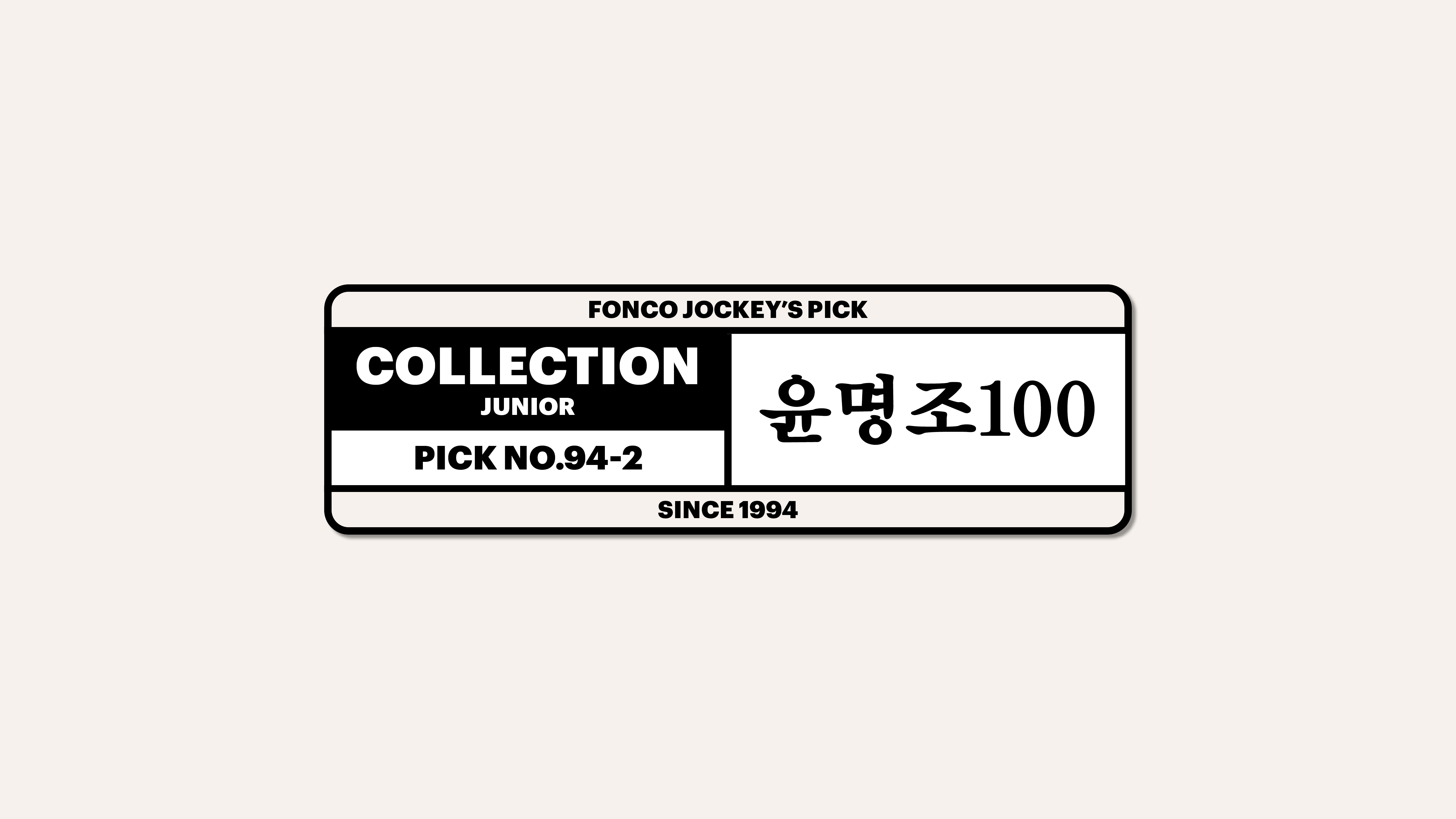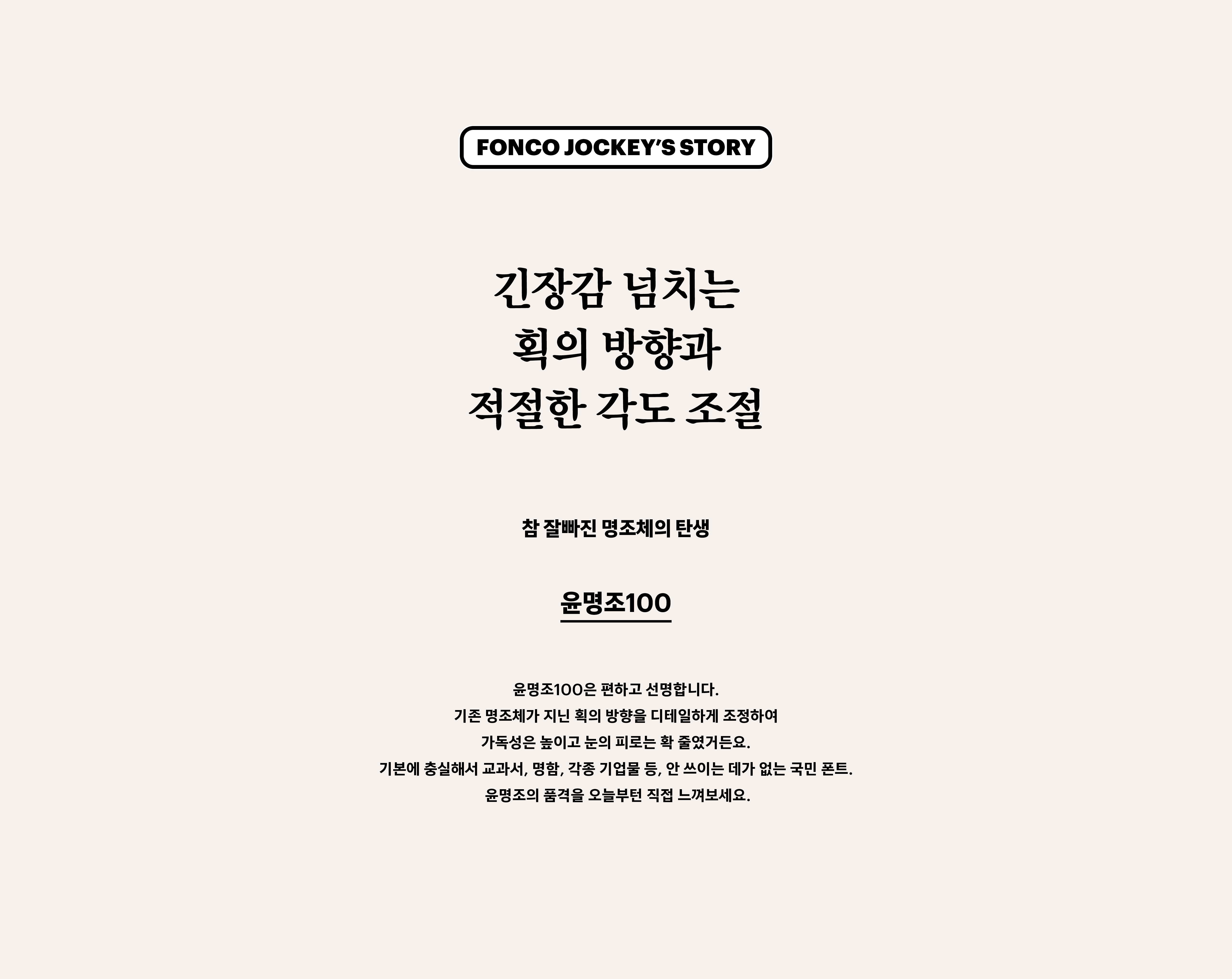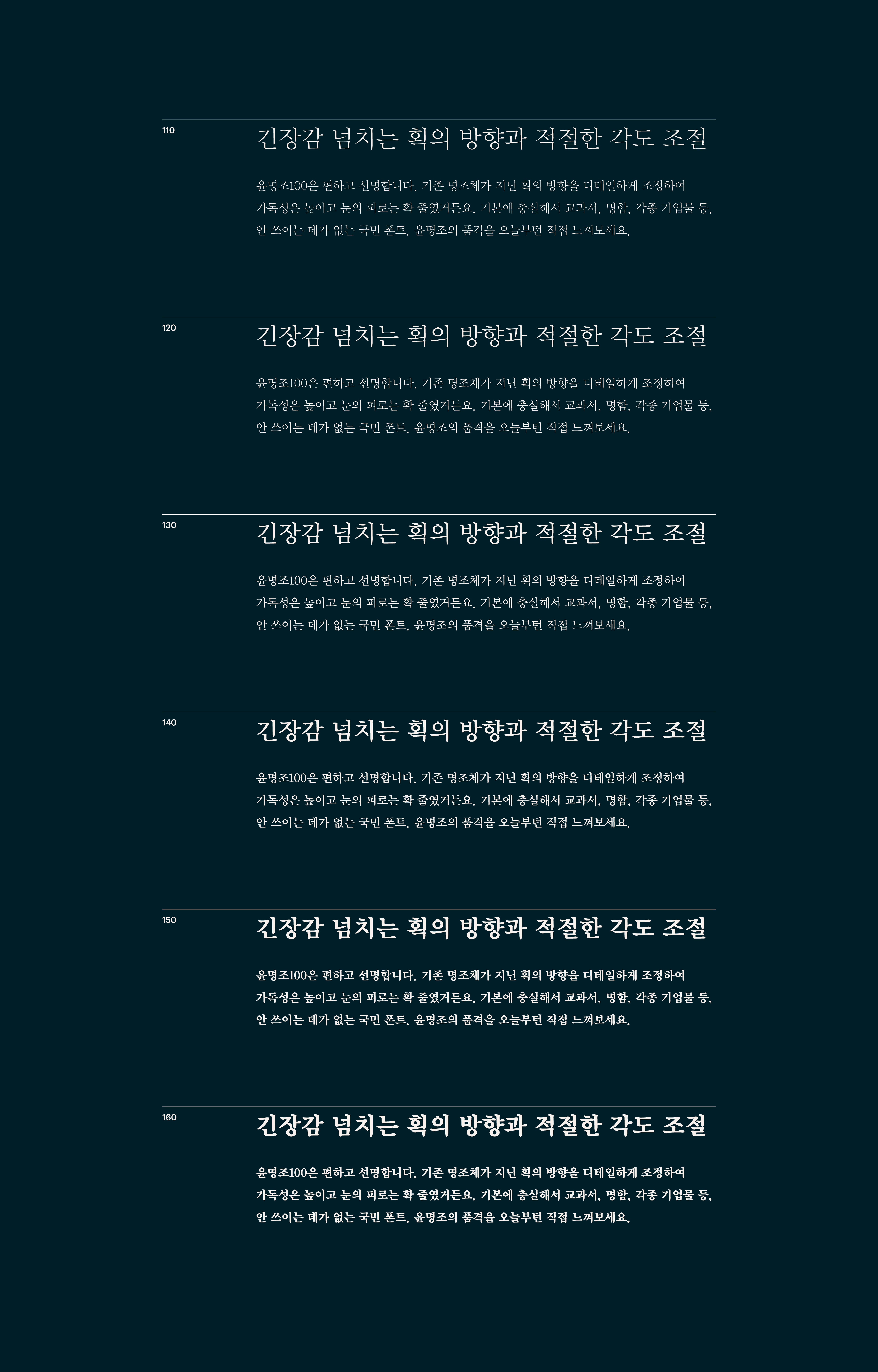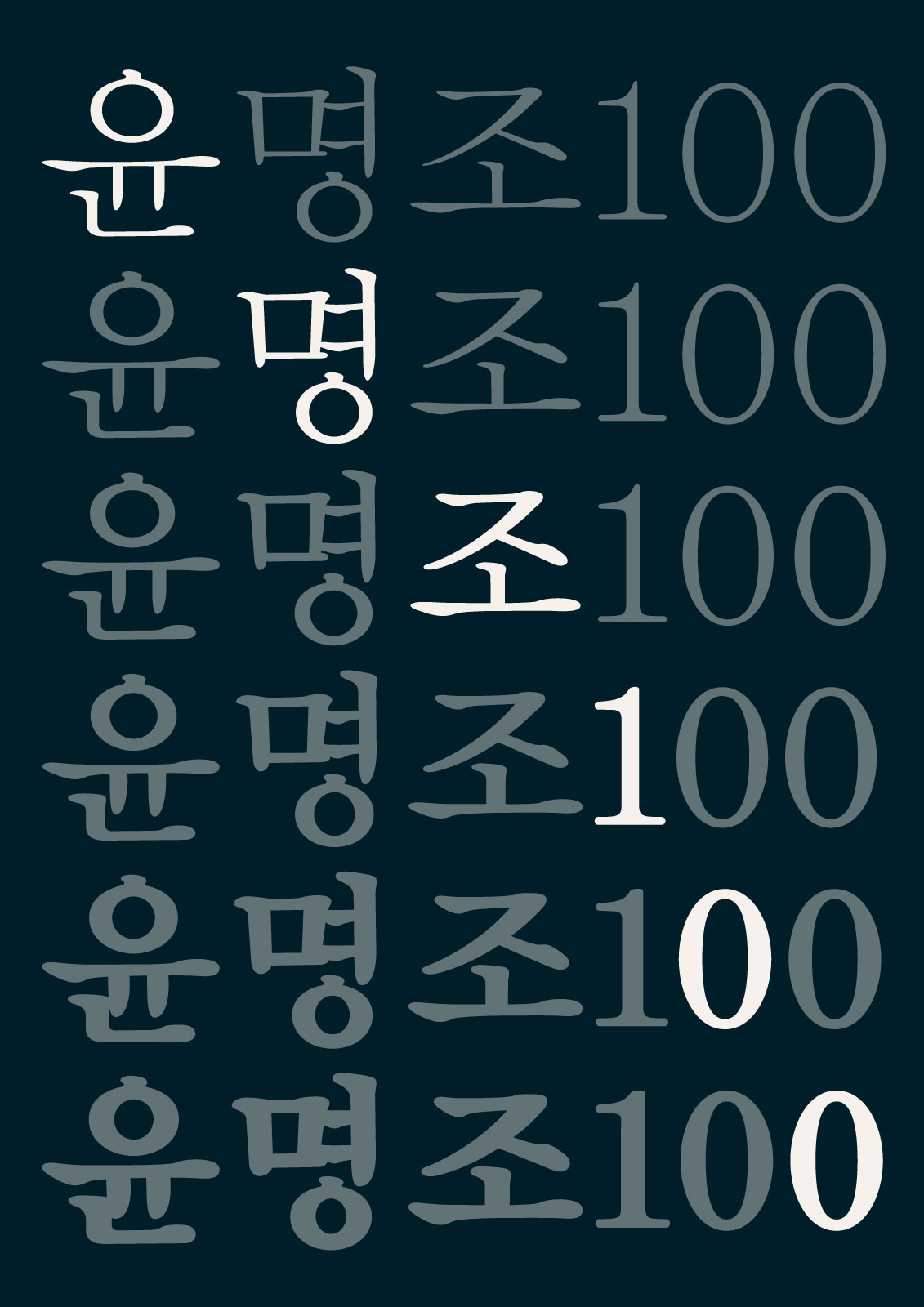
윤명조 100
1990-1994
Yoon 윤명조 100
윤명조100은 편하고 선명합니다. 기존 명조체가 지닌 획의 방향을 디테일하게 조정하여 가독성은 높이고 눈의 피로는 확 줄였거든요. 기본에 충실해서 교과서, 명함, 각종 기업물 등, 안 쓰이는 데가 없는 국민 폰트. 윤명조의 품격을 오늘부턴 직접 느껴보세요.